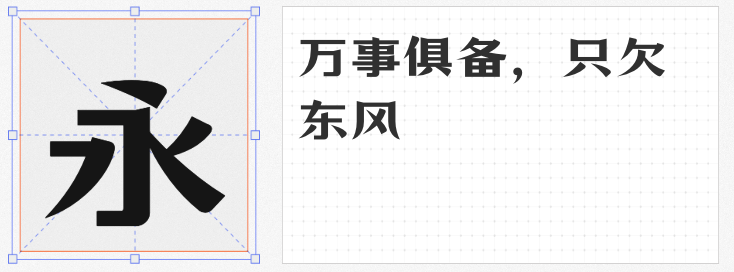
在海报设计中,标题字体是传递品牌调性、吸引视觉焦点的核心元素。今天推荐四款免费商用且适配标题场景的字体,它们风格各异却均具备高辨识度与实用性,助力设计师轻松打造高级感作品。
1. 阿里妈妈数黑体
若需强化科技感或潮流属性,阿里妈妈数黑体是首选。其字形饱满、体态中正,布白设计暗含现代韵律,笔画粗细对比强烈却不失平衡。独特的“图形化”处理让文字兼具阅读性与装饰性,例如撇捺的几何化收尾、横竖的棱角切割,既保留汉字结构,又赋予未来感。适用于互联网、运动品牌或年轻化活动的海报标题,能瞬间传递醒目、先锋的视觉信号。
2. 阿里健康体2.0 中文 85B
作为首款融合中文、注音与盲文的多功能字库,这款字体以人文关怀为内核,字形亲和稳重,笔画简约流畅。其创新点在于通过技术实现盲文点位的标准化嵌入,既满足无障碍阅读需求,又保持整体视觉的和谐统一。适合医疗、公益或教育类海报标题,传递专业感的同时彰显品牌社会责任感。
3. 阿里巴巴普惠体3 95 ExtraBold
专为展现“阿里巴巴少年感”设计的普惠体3,以瘦长字形与高重心结构传递轻盈向上的姿态。笔画简化处理(如省略出脚)强化简洁感,而适当的粗细对比则避免单调。适用于电商促销、快消品或科技类海报标题,能快速抓住眼球,传递年轻、活力的品牌气质。
4. 万事全兴体
脱胎于宋体却融入黑体特征的万事全兴体,兼具古典人文气息与现代简洁感。笔画疏朗有致,转折处保留宋体韵味,整体浑厚庄重却不失灵动。适合酒类、文化或高端消费品牌海报标题,既能体现品牌历史底蕴,又符合当代审美趋势。